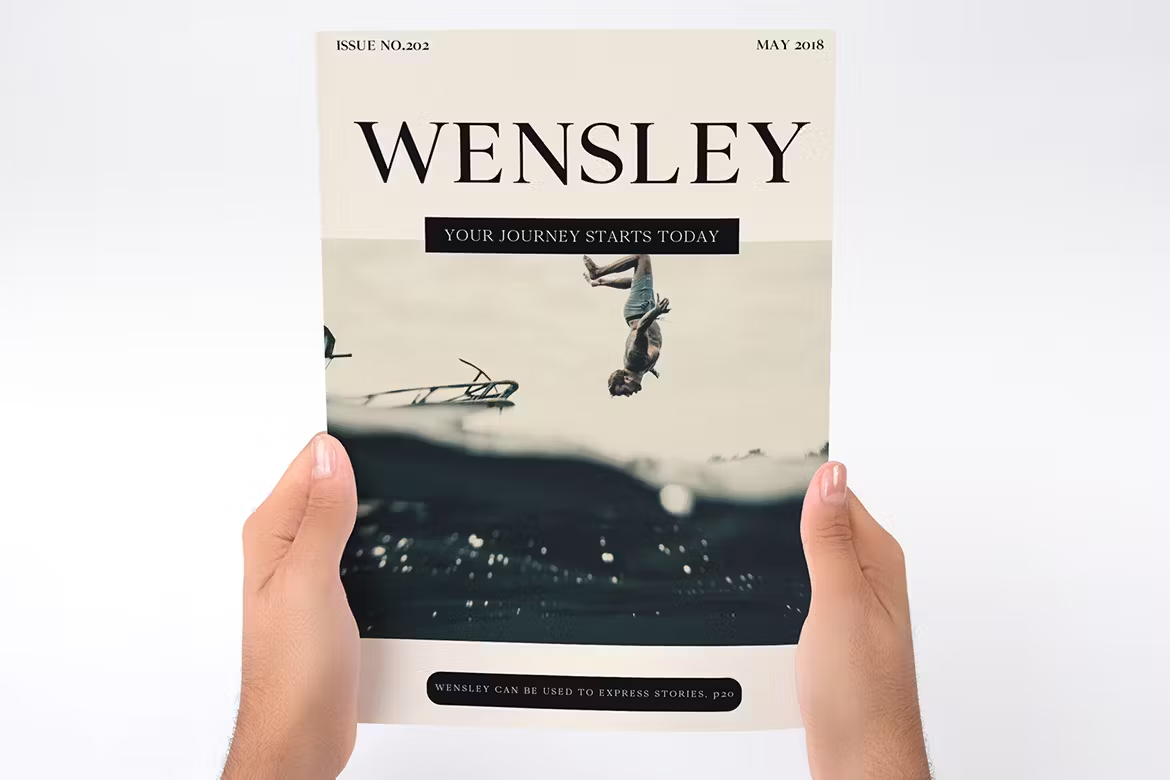
Wensley Font
Description de Wensley Font
Wensley est une famille de polices serif très épurée et simple, parfaite pour apporter de l’élégance à vos créations. Cette police contient tous les alphabets et symboles nécessaires et prend également en charge la plupart des langues autres que l’anglais pour répondre à toutes les exigences linguistiques. L’apparence de Wensley est très traditionnelle et fonctionne parfaitement avec les polices de script, de signature ou d’écriture manuscrite car elle contribue à créer un équilibre entre le moderne et le classique.
Wensley est une police serif très adaptable, adaptée à un large éventail de projets et de domaines. Il est audacieux et très facile à lire et, par conséquent, très approprié pour créer des titres et des titres accrocheurs pour tout média imprimé ou numérique. Pour une utilisation dans des magazines ou des éditoriaux, la sophistication chic de Wensley donnera à vos titres un aspect plus professionnel et raffiné. Les empattements élégants de Wensley sont parfaits pour donner un sentiment de formalité et de sophistication aux logos et aux identités de marque, c’est pourquoi cette police est idéale pour les produits et services haut de gamme. De plus, Wensley excelle dans la présentation, où, grâce à une mise en page claire et élégante, le résultat est propre et présentable. Pour les affiches et les publicités, le grand et puissant Wensley peut vous aider à faire passer votre message et à vous faire remarquer.